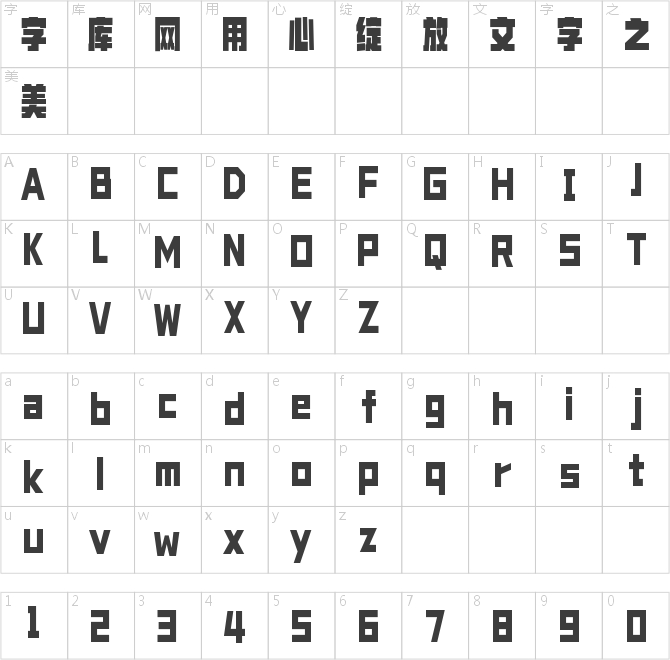
山海潮流時(shí)代黑
山海字庫(kù)
山海潮流時(shí)代黑,是一款綜藝標(biāo)題黑體字體,包含簡(jiǎn)體漢字6763個(gè)。該字體是一款具有強(qiáng)勁視覺(jué)沖擊力的綜藝風(fēng)格標(biāo)題字體。字形瘦高,造型硬朗,全直線的筆畫構(gòu)成棱角分明、堅(jiān)實(shí)有力。